Tschichold, Jan
Deutscher und Schweizer Grafikdesigner, Typograf, Schriftgestalter, Kalligraph, Lehrer und Fachbuchautor. Geboren am 2. April 1902 in Leipzig (Sachsen) als Sohn von Franz und Maria Tzschichhold. Geburtsname »Johannes Tzschichhold«. Gestorben am 11. August 1974 in Locarno (Circolo di Locarno) im Kanton Tessin in der Schweiz.
Jan Tschichold zählt zu den populären Theoretikern der lateinisch geprägten Typografie des 20. Jahrhunderts; er gilt als Meister der traditionellen typografischen Praxis, insbesondere der Buch- und Lesetypografie.
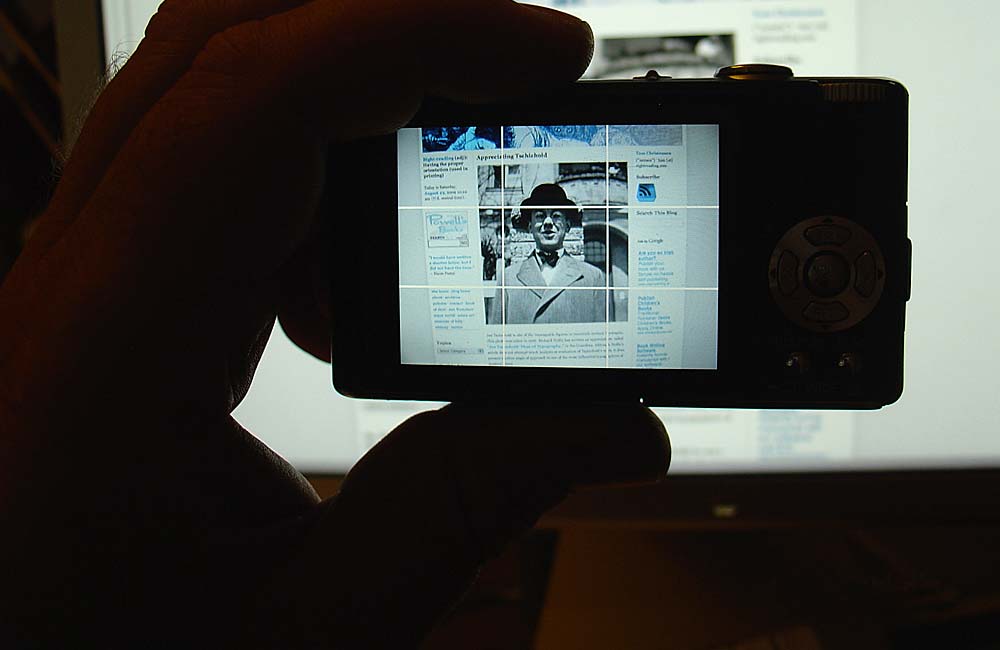
Jan Tschicholds journalistische Tätigkeit machte ab 1923 die »Bauhaustypografie« des Staatlichen Bauhauses, welches 1919 von Walter Gropius (1883–1969) in Weimar als Kunstschule gegründet wurde, weltweit bekannt. Er beeinflusste damit unzählige Grafikdesigner und Typografen, so auch in den 1930er Jahren die »New York School« (siehe Grafikdesign). Insbesondere sein Aufsatz über die neue elementare Typografie, der in den USA in der »Commercial Art« im Juli 1930 unter dem Titel »New Life in Print« erschien, beinflusste viele US-amerikanische Grafiker, u.a. Paul Rand (1914–1996). Tschicholds Ideen über eine »neue typografie« wurden in einer Vielzahl amerikanischer Designhandbücher eingearbeitet, so u.a. in »Modern Typografy and Layout« von Douglas Mc Murtrie oder »Technique of Advertisig Layout« von Frank Young. 1) In seiner zweiten Lebenshälfte distanzierte sich Jan Tschichold spürbar von seinen früheren »jugendlichen« Betrachtungsweisen zur Typografie.
Kindheit im Königreich Sachsen
Seine Kindheit und Jugend verbrachte Johannes Tzschichold in sehr bescheidenen Verhältnissen in Leipzig und Umgebung (Königreich Sachsen), so auch in Grimma, einer kleinen Stadt zwischen Leipzig, Chemnitz und Dresden, wo er nach der Volksschule kurzweilig das »Königliche Lehrerseminar Grimma« (ab 1924 umbenannt in »Deutsche Oberschule«) 2) besuchte.
Tschicholds Vater Franz Tzschichhold arbeitete zu dieser Zeit als Schriftenmaler in Leipzig. Er soll seine Leidenschaft zur Kalligraphie geweckt haben. 3) Seine Mutter Maria war eine geborene Zapff. Die Großeltern väterlicherseits stammten aus Pförden bei Forst in der Niederlausitz, einem Ort östlich der Neiße, heute Brody, Polen.
Jugend in der Weimarer Republik
Unmittelbar nach dem Ende des Ersten Weltkriegs (1914–1918), der Abschaffung der Monarchie (1918) und der Gründung der Weimarer Republik (1918–1933) wird der 17. jährige Johannes Tzschichold 1919 in die Vorklasse des bekannten Paläographen, Typografen und Kalligraphen Hermann Delitsch (1869–1937) an der »Akademie für Graphische Künste und Buchgewerbe« in Leipzig (ab 1950 »Hochschule für Grafik und Buchkunst Leipzig«) aufgenommen. Im Anschluss besuchte er von 1920 bis 1921 die Kunstgewerbeschule in Dresden. 1921 wechselt Johannes Tzschichold dann wieder nach Leipzig als Schüler in die Meisterklasse »Buchgewerbe, Illustration, freie und angewandte Graphik« des Buchkünstlers, Typografen und Grafikdesigners Dr. h.c. Walter Tiemann (1876–1951), der von 1921 bis 1941 Direktor der Königlichen Akademie für graphische Künste und Buchgewerbe in Leipzig war.
Tiemann wurde ab Mitte der 1920er Jahre sowohl von nationalkonservativen Kollegen als auch vom jungen revolutionären »jan tschichold« im Zuge des Dogmas »neue typografie« vehement attackiert. 1940 wurde Tiemann von den Nationalsozialisten »zum vorläufigen Ruhestand« gezwungen.
Tschichold schreibt später über sich selbst, beispielsweise 1946 in seinem Aufsatz »Glaube und Wirklichkeit«, dass er »von 1920 bis 1925 Lehrer der Schrift an der Akademie für graphische Künste und Buchgewerbe in Leipzig gewesen war«. Das ist natürlich nicht korrekt. Tschichold hatte im Auftrag seines einstigen Mentors Tiemann vertretungsweise nur einige Abendkurse im Schriftschreiben betreut, da aufgrund der katastrophalen Auswirkungen des 1. Weltkriegs und der revolutionären Unruhen im neuen »Freistaat Sachsen« akuter Lehrermangel bestand. Er war dort Schüler, kein »Lehrer«. Die Bezeichnungen Tutor oder Assistent wären sicherlich für eine derartige »Lehrtätigkeit« angemessener. Dieser Form der Selbstinszenierung wird Jan Tschichold allerdings bis ins hohe Alter treu bleiben. Im Laufe seines Lebens wird er noch die eine oder andere Realität geschickt zu seinen Gunsten umformulieren, verschweigen oder betonen. So schrieb beispielsweise Jan Tschichold 1972 ungeniert in den Typografischen Monatsblättern 4) unter dem Pseudonym »Reminiscor« seine eigene »Geburtstagslaudatio«; laut Max Caflisch (1916–2004) möglicherweise auch deshalb, »(…) weil er der Auffassung war, niemand anders sei in der Lage, einen solchen Beitrag zu schreiben – und so gut zu schreiben …«.
Ab den frühen 1920er Jahren ist Johannes Tzschichold neben seinem Studium auch als freiberufliche »Typografischer Entwerfer« tätig, u.a. für den Leipziger Gebrauchsgraphiker Erich Gruner (1881–1966), der zu jener Zeit einer der führenden Grafiker Leipzigs war. Gruner entwarf beispielsweise 1917 das Doppel-M-Signet (MusterMesse) für die Leipziger Messe. Tzschichold entwarf für Gruner kalligraphisch geschriebene Inserate für die Leipziger Messe.
Des Weiteren arbeitete er für die Leipziger Buchdruckerei Fischer & Wittig und den Leipziger Insel-Verlag, der u.a. bei der Offizin Poeschel & Trepte in Leipzig produzierte (heute Schäffer-Poeschel Verlag für Wirtschaft, Steuern, Recht GmbH, Stuttgart. Ein Unternehmen der Verlagsgruppe Handelsblatt, Düsseldorf), wo Tzschichold als Volontär im Akzidenzsatz und in der Werksatzabteilung seine ersten praktischen Kenntnisse im Handschriftsatz sammelte.
Anfang der 1920er Jahre knüpft Johannes Tzschichold als Protegé seines renommierten Lehrers Walter Tiemann Kontakte zur Offenbacher Schriftgießerei der Gebrüder Klingspor (gegründet von Karl Klingspor, 1868–1950, infolge Stempel AG, infolge Linotype®, infolge Monotype®), so u.a. auch zu dem damals sehr prominenten Offenbacher Typografen Rudolf Koch (1876–1934), einem Bekannten von Tiemann. Walter Tiemann veröffentlichte ab 1909 seine Druckschriften bei der Offenbacher Schriftgießerei der Gebrüder Klingspor, für die auch Rudolf Koch arbeitete. Beispielsweise publizierte 1914 Koch dort die Schrift »Maximilian« und Tieman die Schrift »Peter Schlemihl«.
Ungefähr im Alter von 20 Jahren wird Johannes Tzschichhold mit den avantgarden Betrachtungsweisen des Futurismus, Dadaismus und Konstruktivismus konfrontiert. Insbesondere faszinierten ihn die Zielsetzungen und Formensprachen des 1907 in München gegründeten Deutschen Werkbunds und des 1919 in Weimar gegründeten Bauhauses, der beiden Keimzellen der modernen »Visuellen Gestaltung« und der »Modernen Typografie« (siehe auch Schriftgeschichte, Typografie und Grotesk).